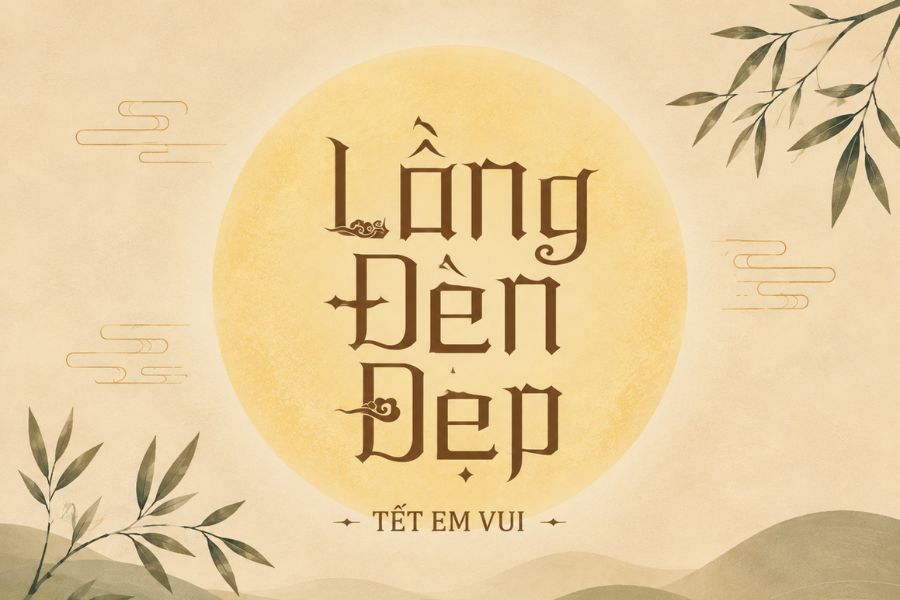
Font chữ Trung thu đẹp giúp thiết kế bao bì, banner hay thiệp chúc trở nên nổi bật và giàu không khí lễ hội hơn. Tuy nhiên, không phải font nào cũng hỗ trợ tiếng Việt đầy đủ hoặc giữ được độ sắc nét khi đưa vào in ấn. Ở bài viết này, Doozypack.vn gợi ý các font chữ Trung thu đẹp, miễn phí cùng các lưu ý quan trọng khi ứng dụng vào thiết kế và sản xuất bao bì.
Font chữ Trung thu là phông chữ có phong cách phù hợp với các thiết kế lấy chủ đề Tết Trung thu. Khác với font văn bản thiên về khả năng đọc, nhóm font này chú trọng nhiều hơn đến cảm xúc thị giác và tính trang trí.
Bạn dễ dàng bắt gặp những nét chữ mềm như dải mây, đường cong gợi hình trăng khuyết hay kiểu chữ tròn đầy liên tưởng đến vầng trăng rằm tháng Tám. Một số font chữ Trung thu đẹp lấy cảm hứng từ thư pháp và nét bút lông truyền thống, tạo cảm giác hoài cổ, ấm áp nhưng vẫn đủ nổi bật khi đặt trên bao bì hiện đại.
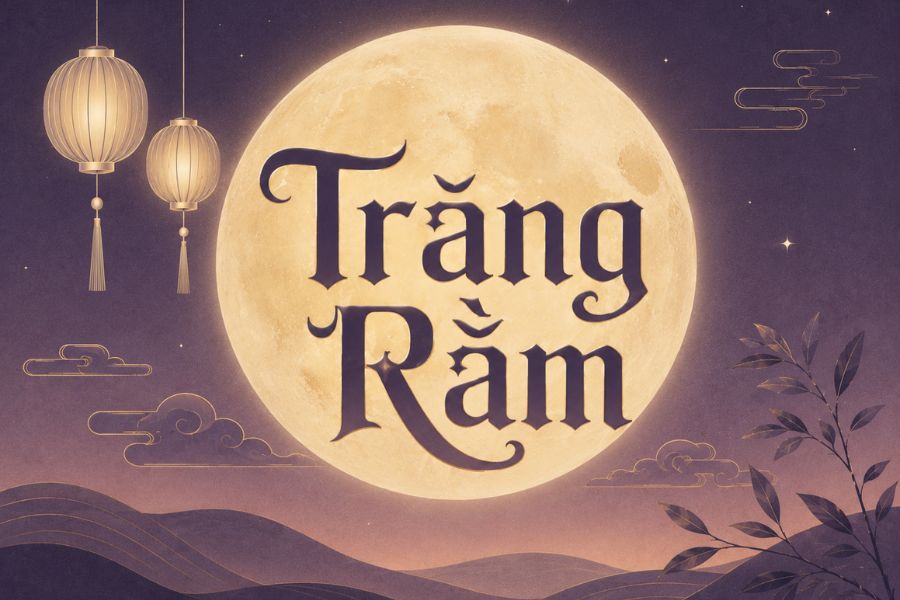
Tùy phong cách thiết kế, font Trung thu được ứng dụng theo một số hướng:
- Thư pháp truyền thống: Phù hợp với hộp bánh, thiệp chúc Tết Đoàn viên và các thiết kế mang màu sắc Á Đông.
- Nét tròn, mềm mại: Tạo cảm giác gần gũi, vui tươi, thích hợp với sản phẩm dành cho gia đình hoặc trẻ em.
- Font display cách điệu: Dùng cho tiêu đề, tên bộ sưu tập và các chiến dịch truyền thông cần khả năng nhận diện cao.
- Phong cách cổ điển: Kết hợp tốt với họa tiết cung trăng, đèn lồng, hoa sen, cá chép hay kiến trúc truyền thống.
Với nội dung tiếng Việt, khả năng hiển thị đầy đủ dấu thanh và các ký tự như ă, â, ê, ô, ơ, ư, đ đặc biệt quan trọng. Nhiều font quốc tế trông rất đẹp ở bản demo nhưng lại thiếu glyph tiếng Việt.
Khi nhập những cụm từ như “Tết Đoàn Viên”, “Trăng Rằm Tháng Tám” hoặc “Trung Thu Sum Vầy”, dấu có thể sai vị trí, khác kiểu nét hoặc thậm chí không hiển thị. Điều này khiến thiết kế thiếu đồng nhất và dễ phát sinh lỗi khi đưa vào sản xuất. Vì vậy, font chữ Việt hóa Trung thu tốt cần được xử lý dấu hài hòa với form chữ gốc, bảo đảm khoảng cách, tỷ lệ và đường nét vẫn đẹp khi sử dụng ở kích thước lớn.
5 ứng dụng font chữ Trung thu trong thiết kế và in ấn
Font chữ Trung thu đẹp có thể tạo điểm nhấn cho nhiều ấn phẩm mùa lễ hội. Trong thực tế, font được ứng dụng vào:
- Bao bì hộp bánh Trung thu: Dùng cho tên bộ sưu tập, lời chúc hoặc thông điệp trên nắp hộp. Font thư pháp kết hợp ép kim, dập nổi giúp bao bì thêm sang trọng.
- Túi giấy đựng quà: Sử dụng đồng bộ font với hộp bánh giúp tăng tính nhất quán và khả năng nhận diện thương hiệu.
- Backdrop, banner sự kiện: Các kiểu chữ cách điệu phù hợp với tiêu đề như “Đêm Hội Trăng Rằm”, “Trung Thu Đoàn Viên”, tạo điểm nhìn từ xa.
- Thiệp và voucher: Font chữ Trung Thu Việt hóa giúp lời chúc hiển thị đầy đủ dấu, đẹp mắt và mang đậm không khí ngày hội.
- Quà tặng doanh nghiệp: Có thể ứng dụng trên ấm chén, cốc sứ, hộp gỗ, túi vải hoặc tem nhãn. Khi in hoặc khắc, nên ưu tiên font có đường nét rõ để hạn chế mất chi tiết.
Lưu ý: Chỉ nên dùng font nghệ thuật cho tiêu đề hoặc thông điệp ngắn. Phần nội dung dài nên kết hợp font dễ đọc để thiết kế vừa có điểm nhấn, vừa đảm bảo trải nghiệm thị giác.
Khi sử dụng font chữ Việt hóa Trung Thu đồng bộ trên hộp, túi, thiệp và quà tặng, doanh nghiệp cũng dễ xây dựng hệ thống nhận diện mùa lễ hội chỉn chu hơn.
- Kiểm tra độ dày nét chữ: Khi in trên giấy nhám, túi vải hoặc ép kim, nét quá mảnh có thể bị mất. Hãy tăng nhẹ độ dày nếu cần nhưng vẫn giữ đúng đặc trưng của font.
- Tối ưu đường vector: Với kỹ thuật dập nổi, ép kim hoặc cắt laser, nên làm mượt các điểm neo và loại bỏ path thừa để đường nét thành phẩm sắc sảo hơn.